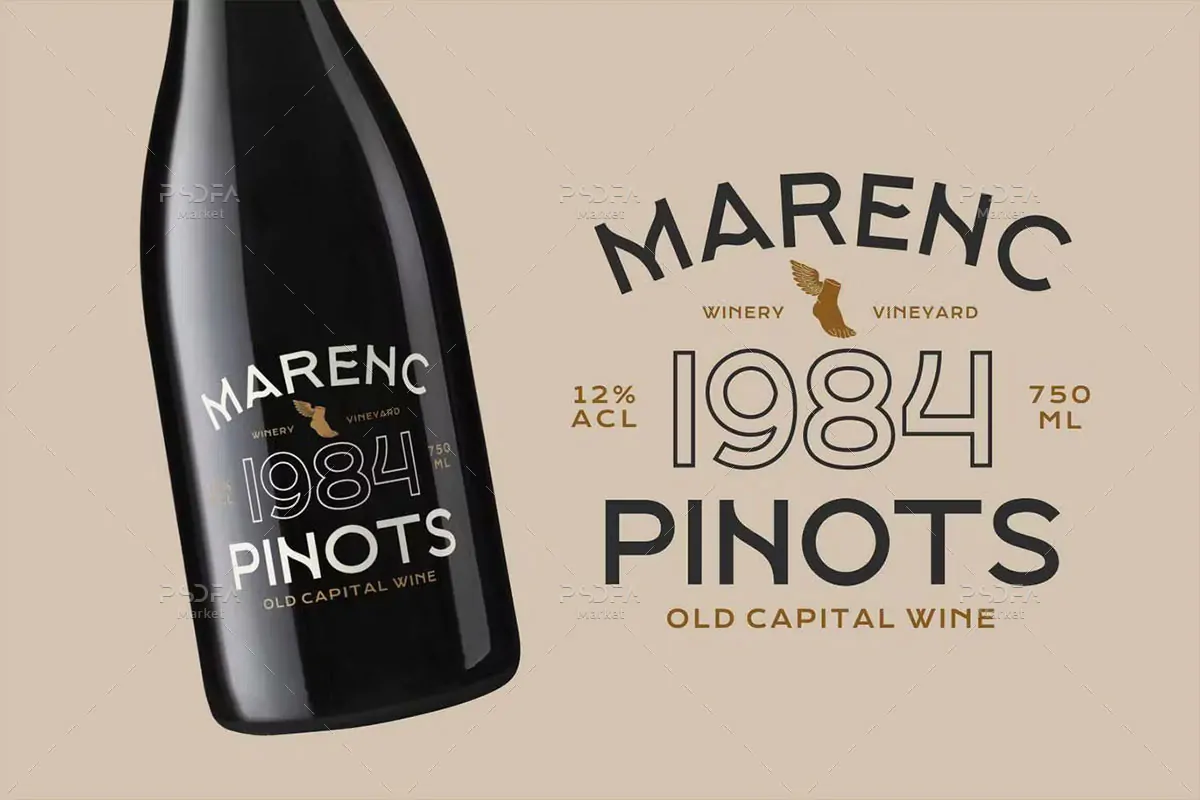
فونت کلاسیک و قدیمی Cemains
فونت کلاسیک و قدیمی
فونت کلاسیک و قدیمی Cemains یک قلم سنس سریف انگلیسی است که مناسب جهت استفاده در طرح و پروژههای گرافیکی مختلف میباشد. فونت Cemains با وزن معمولی طراحی شده است که میتوانید از آن در طراحی انواع پوستر، بسته بندی محصولات، ظروف یکبار مصرف، آرایشی و بهداشتی و … استفاده کنید.